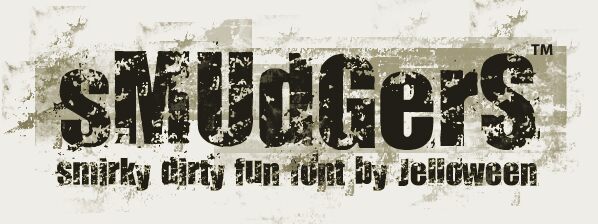
Smudgers autorstwa Tjarda Koster to darmowy font typu grunge display, który wygląda, jakby został przetarty, zarysowany i rozmazany na literach. Jego ciężkie, zaokrąglone formy zachowują wyrazisty kształt, podczas gdy poszarpane krawędzie i nieregularne luki nadają mu brudny, uliczny charakter, przypominający bardziej ślady atramentu niż starannie nałożony efekt postarzania.
Świetnie sprawdza się na plakatach koncertowych, okładkach zinów, grafikach deskorolkowych, okładkach albumów oraz w tytułach w stylu horroru, gdzie surowy wygląd liczy się bardziej niż gładkość. Jako darmowy font, sprawdza się również w krótkich nagłówkach, napisach na naszywkach czy projektach logotypów, które potrzebują mocnej sylwetki z odpowiednią dawką niedoskonałości, aby wyglądać na niespokojne i wykonane ręcznie.